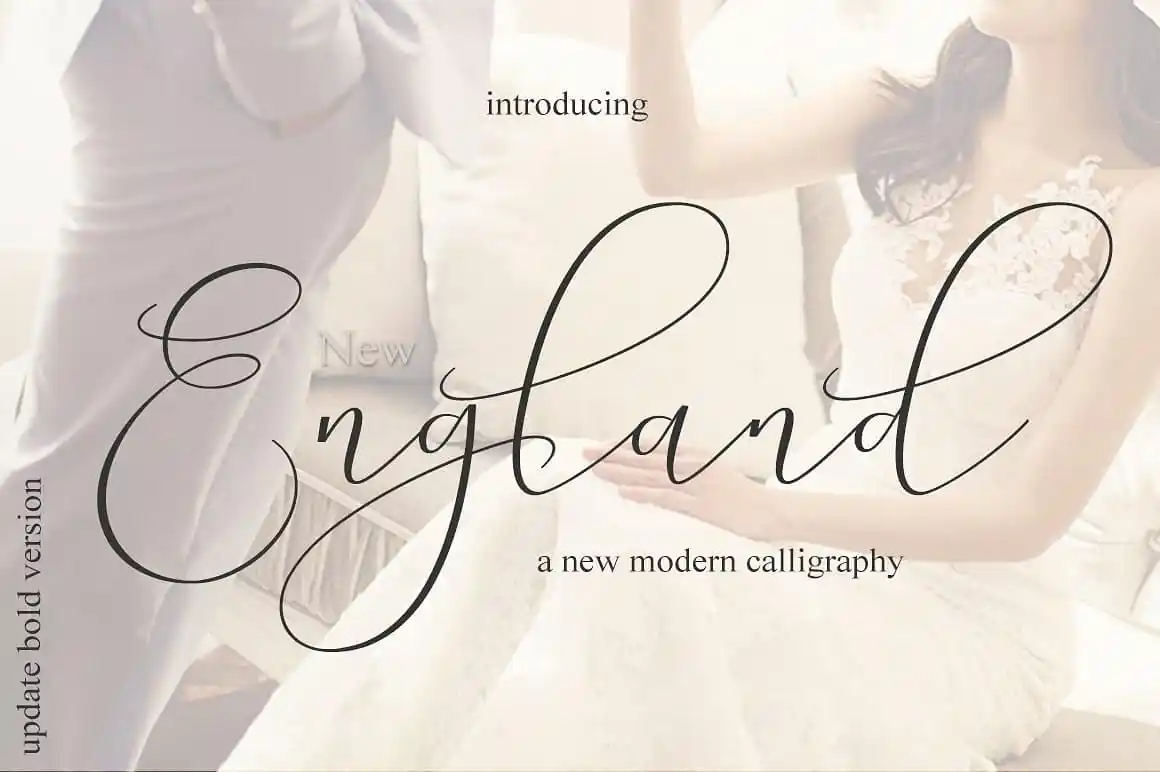
New England Script Font – Download Grátis
Nova Engmódia é uma elegante tipografia moderna com estilo de escrita, criada por MrLetters para os amantes da chamada ou qualquer designer que esteja procurando uma fonte sofisticada e moderna. Com sua face levemente suave, essa fonte parece perfeitamente em sintonia com diferentes estilos de criação. Perfeita tanto para criar assinaturas elegantes quanto logos e fotografias, a New England Script Font também oferece um aspecto encantador quando usada nos estilos de iluminação neon colorida. É uma opção ideal para designers buscando dar vida às suas criações com um toque personalizado, desde o estilo clássico até temas como beleza e produtos. Sem dúvida, essa fonte é uma excelente adição a qualquer projeto que esteja buscando incorporar um aspecto criativo e sofisticado.